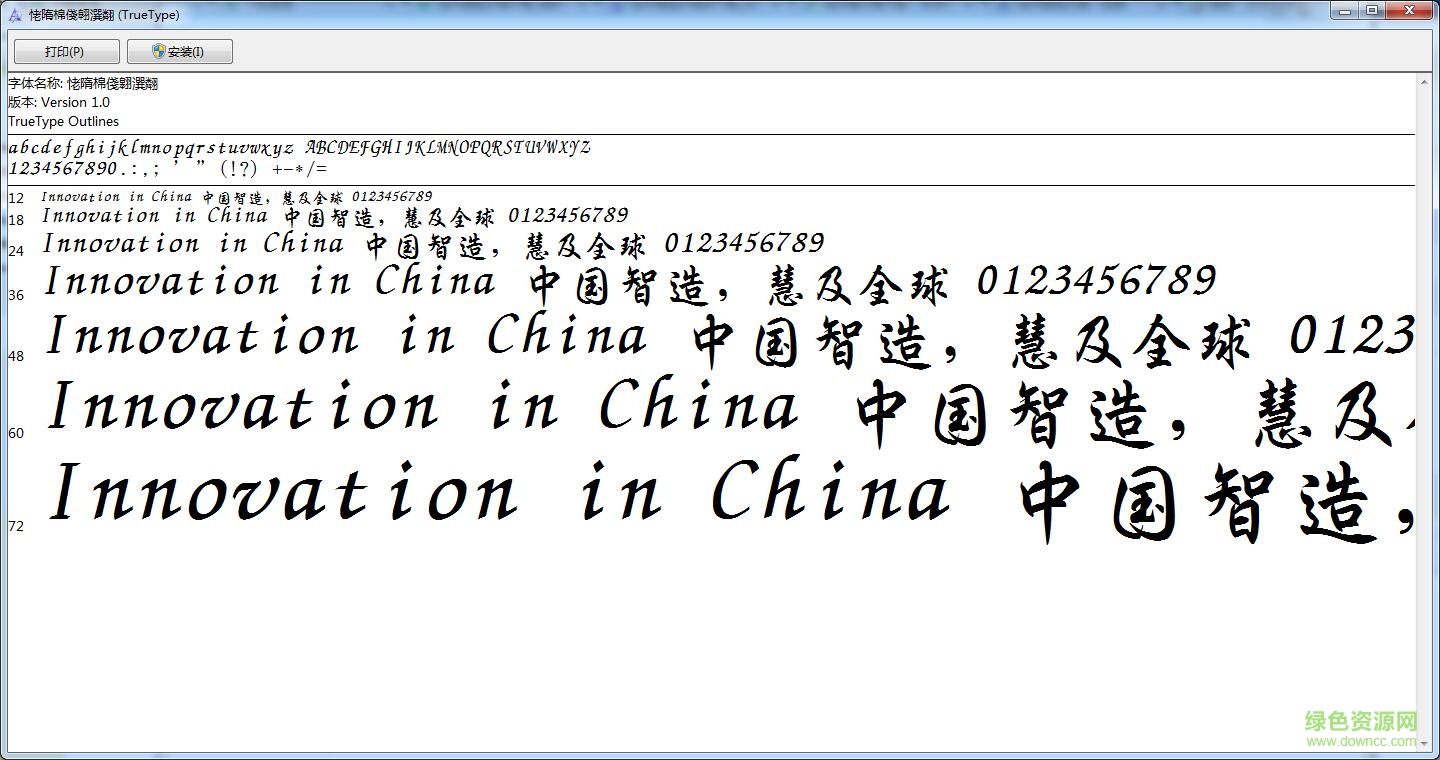
迷你簡行楷碑字體是一種介于楷體、行書之間的迷你字體!小編提供的這款字體非常美觀大氣,為大家提供了簡單的安裝方法,歡迎大家到綠色資源網(wǎng)下載使用!
迷你簡粗行楷是一款簡體的楷體字,本款字體偏向于行書,字體端正、大氣,連筆流暢又不失整潔,如果你喜歡這款字體,就來綠色資源網(wǎng)免費下載吧!